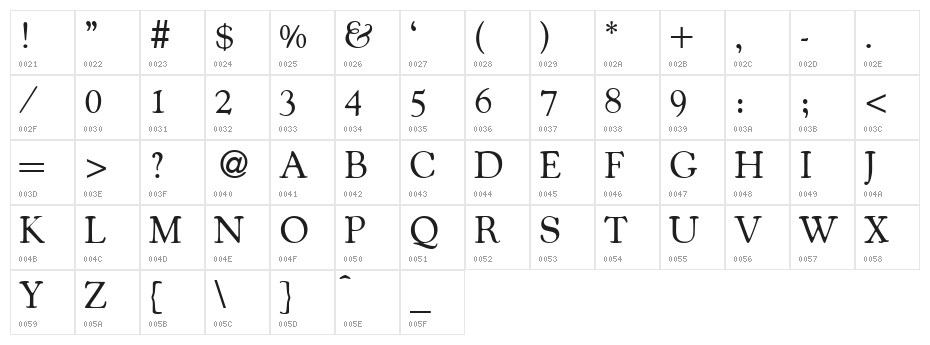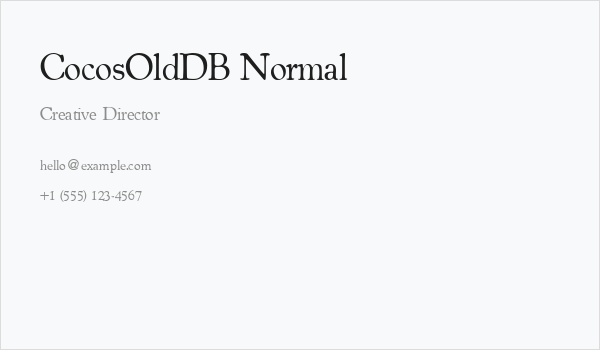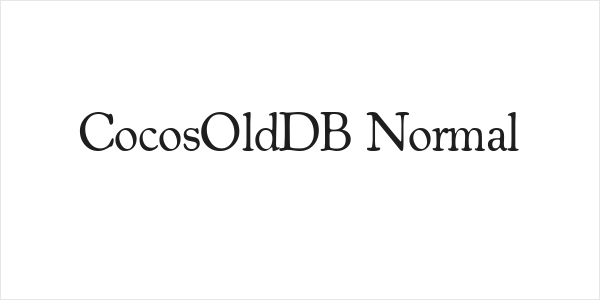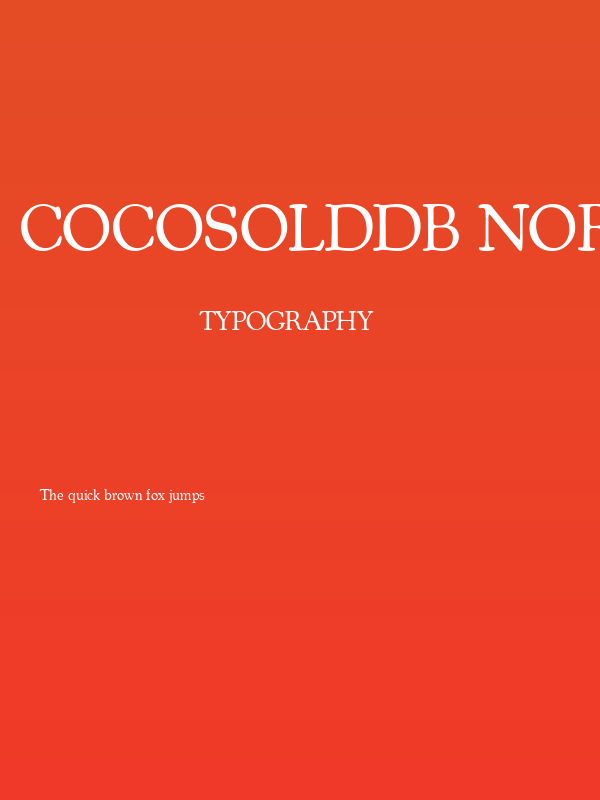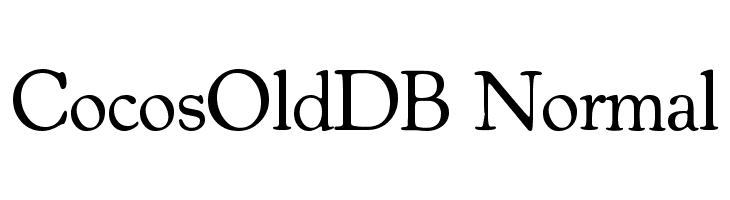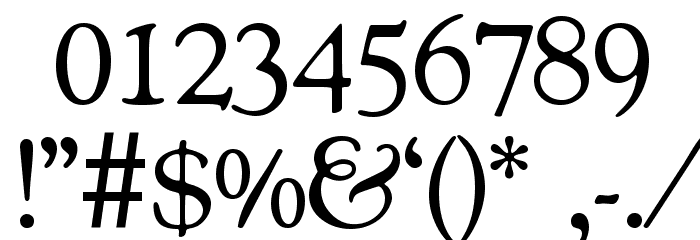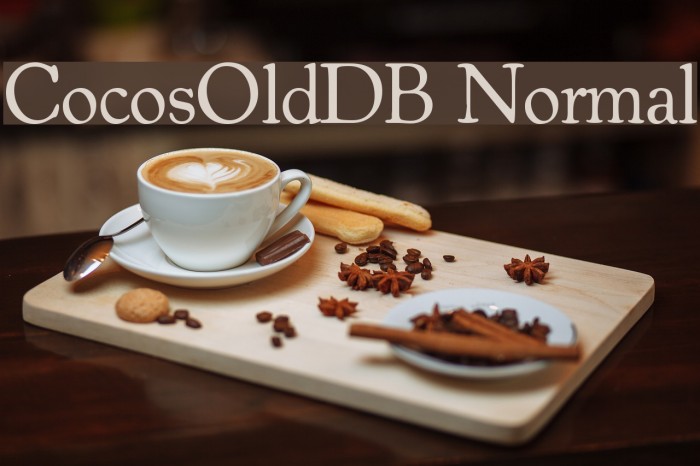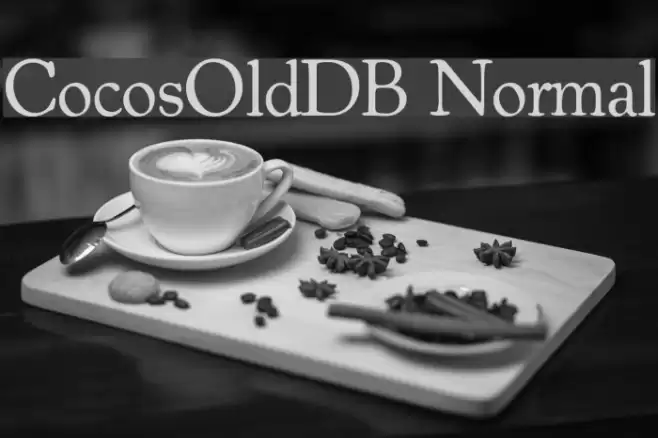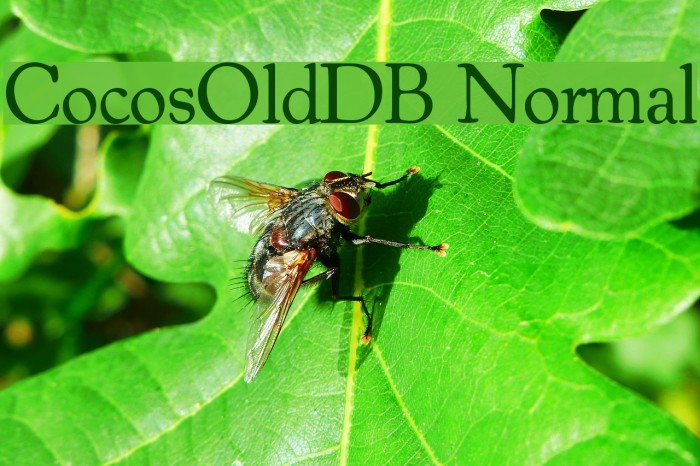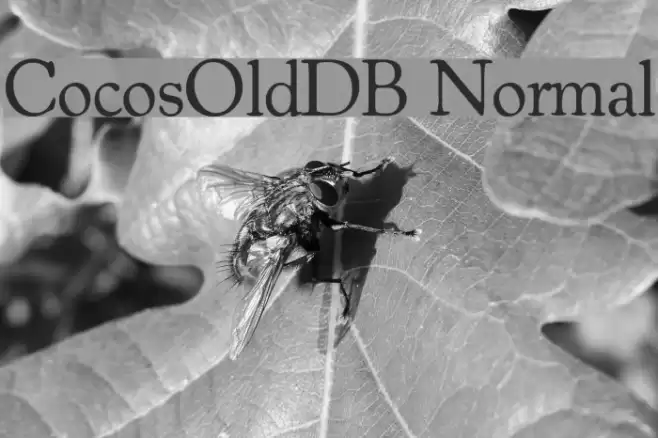
CocosOldDB Normal Font
| الاسم | CocosOldDB Normal |
| الوزن | Normal |
| النمط العام | Classic |
| حالة الاستخدام | Headlines, Body text, Logos |
| مشاريع مقترحة | Ideal for book covers, editorial design, formal invitations, and branding projects that require a touch of elegance. |